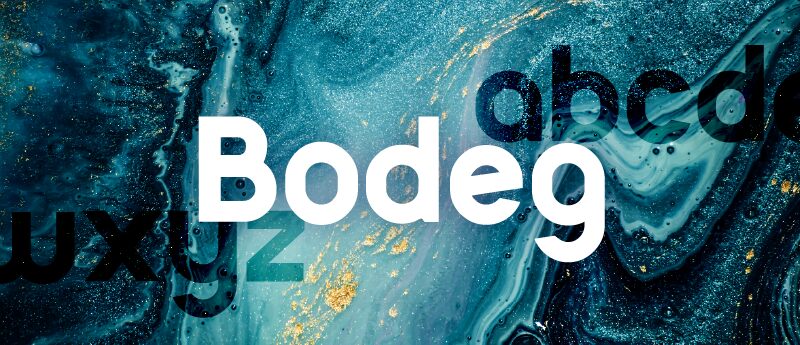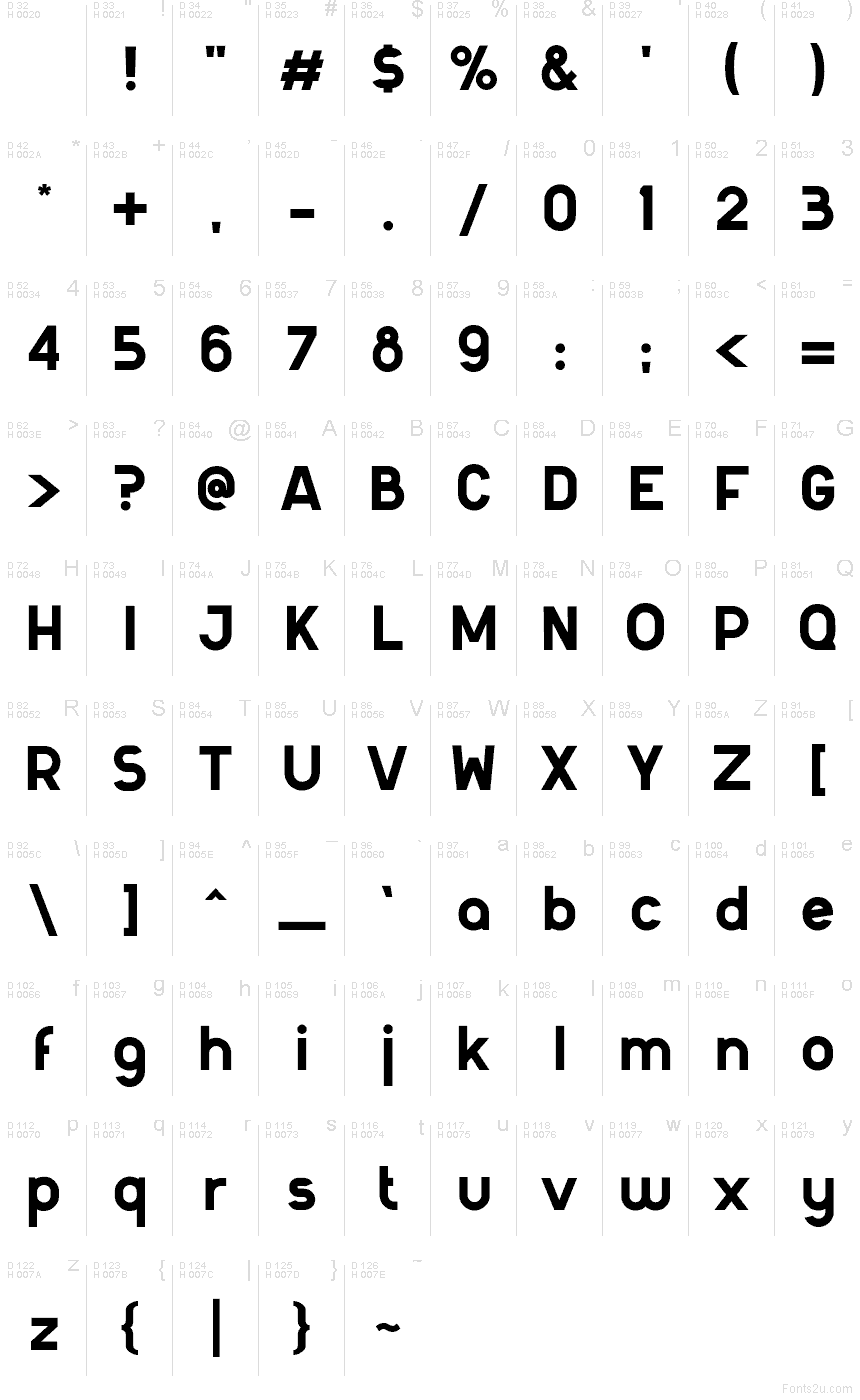
Bodeg
Bodeg, de Nermin Kahrimanovic, es una tipografía sans serif geométrica gratuita con un aspecto pesado, casi monolineal, y formas anchas y redondeadas. Las letras se sienten compactas y amigables, pero el corte de la «e» y la altura y limpieza de la «d» y la «g» evitan que el diseño se vea blando, dotando a la fuente de una voz contundente y contemporánea que resulta más gráfica que neutral.
Encaja perfectamente en proyectos de branding, titulares de pósteres, packaging, portadas y carteles donde las palabras cortas necesiten una presencia sólida y rotunda. Al ser una fuente gratuita, Bodeg también es ideal para logotipos y señalética, ya que sus formas circulares sencillas y sus verticales rectas crean un ritmo nítido incluso en composiciones breves.